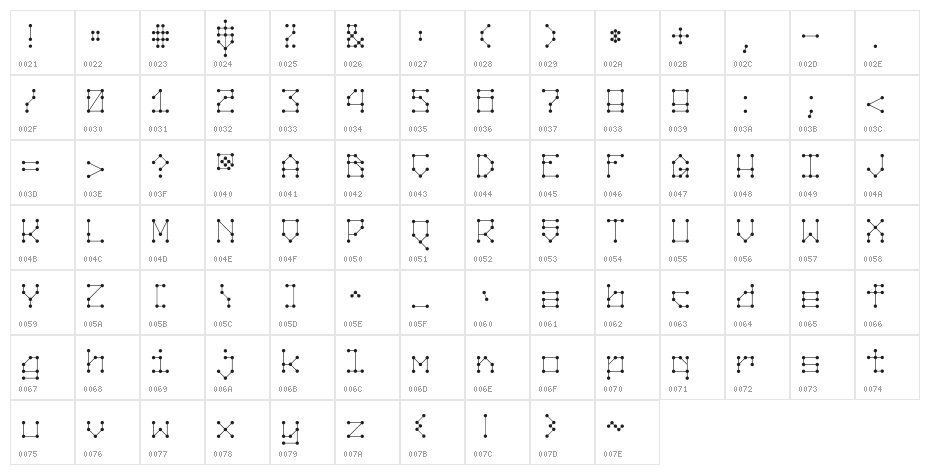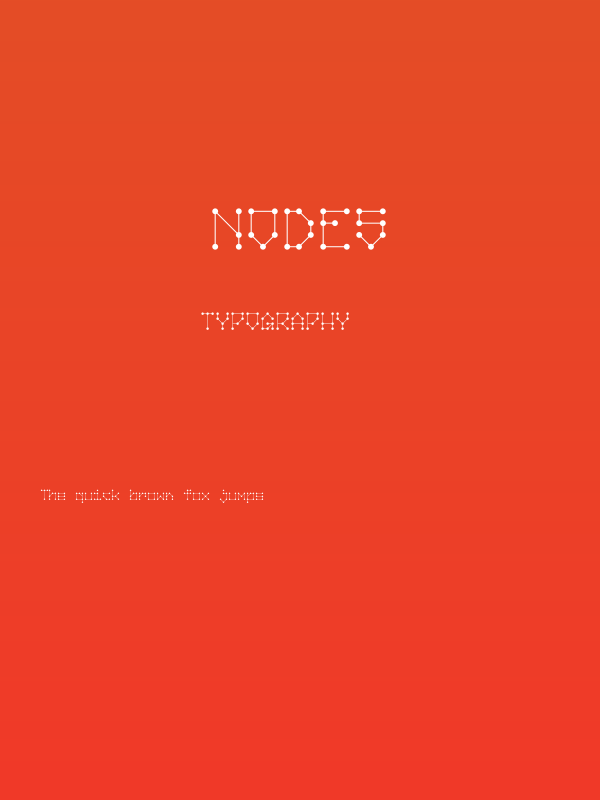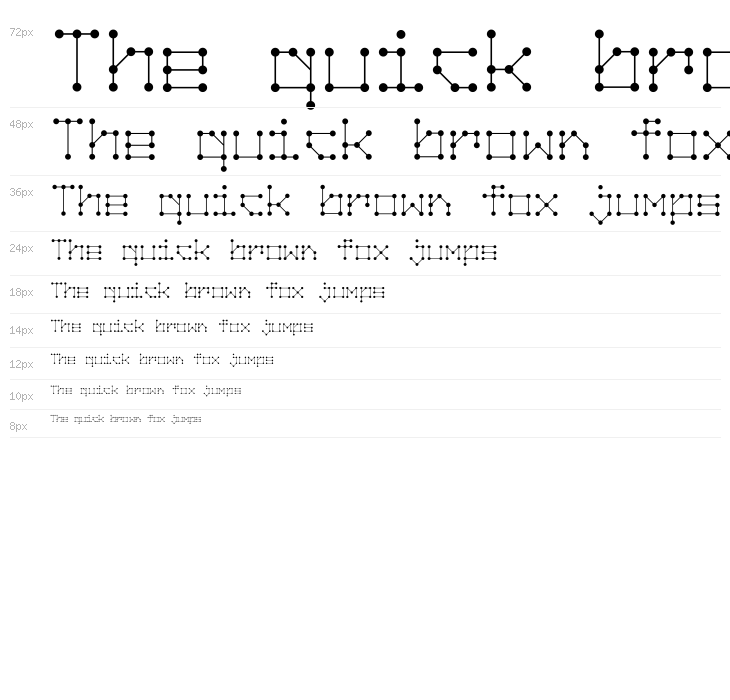
NODES Font
| Kategorien | Futuristic |
| Zeichenabstand | Normal |
| Anwendungsfall | Logos, Headlines, Posters |
| Vorgeschlagene Projekte | Ideal for tech-related branding, digital art projects, futuristic designs, and educational materials focusing on networks or connectivity. |